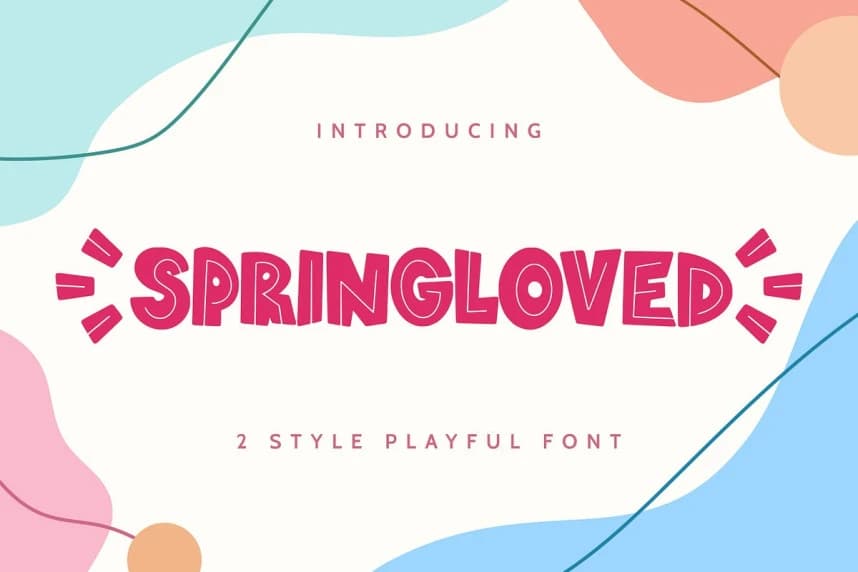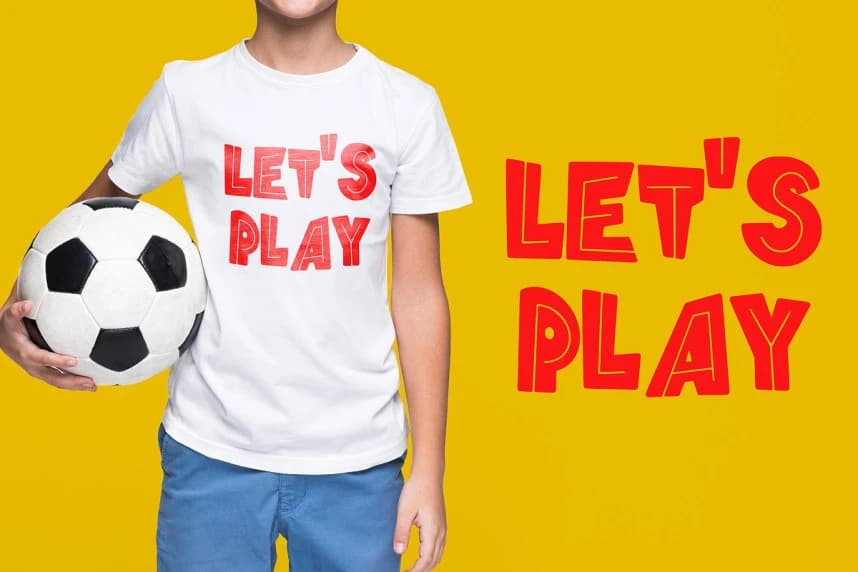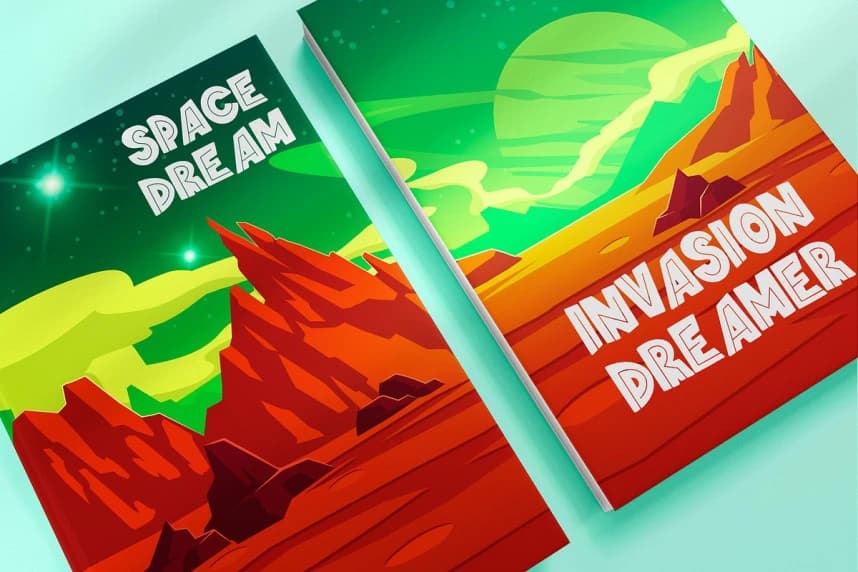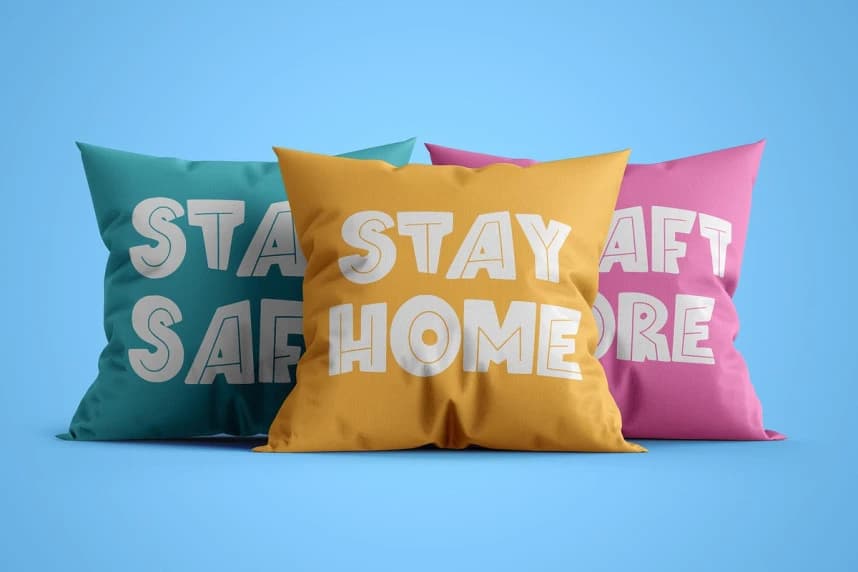
Springloved Playful Font
Springloved Playful Font, sevimli bir display yazı tipidir ve gerçek bir favori olması için özenle tasarlandı. Rahat cazibesi onu son derece doğal, okunabilir ve nihayetinde inanılmaz derecede çok yönlü kılar. Springloved her bağlamda harika görünecek.
Springloved Playful Font, sevimli bir gösterim yazı tipidir ve gerçek bir favori olmak için özenle tasarlanmıştır. Sıradan cazibesi onu doğal, okunabilir ve nihayetinde son derece çok yönlü kılar. Springloved her bağlamda etkileyici görünecek.